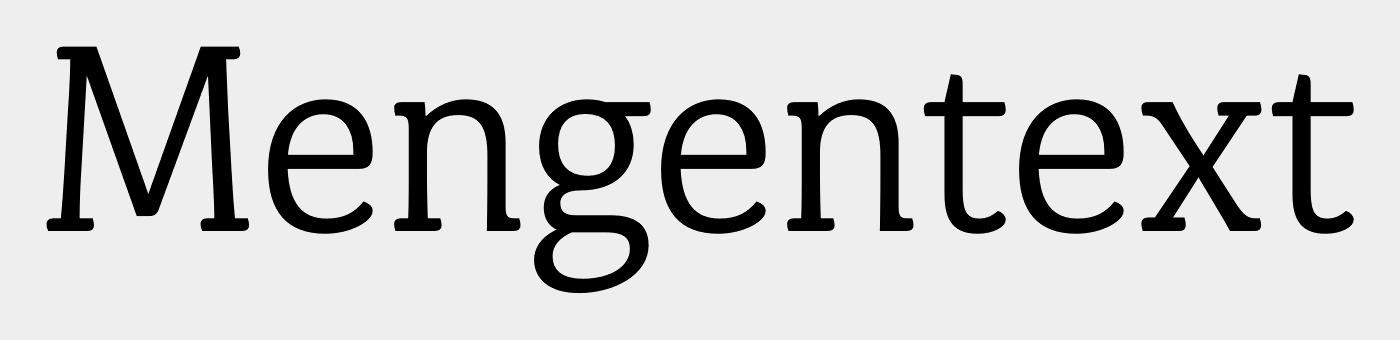
Gesucht: Font für Mengentext in lateinischer Schrift, vollständige diakritische Zeichen, Griechisch, Hebräisch, Arabisch, Äthiopisch
Wahrscheinlich suche ich die eierlegende Wollmilchsau, aber vielleicht gibt es ja die Schrift, die ich mit der Antipode von Paul Hanslow (http://typefacedesign.net/typefaces/year/2017/antipode/) bereits gefunden glaubte -- bis mir klar wurde, dass es die Antipode nur als Projekt, nicht aber als fertigen Font bzw. Fontfamilie gibt. Bestätigt wurde dies in einem sehr netten Mail-Austausch mit Paul,  den es derweil wohl ans andere Ende der Welt verschlagen hat (Kanada) und der zwar weiter an dem Projekt arbeitet, es aber noch nicht veröffentlichungsreif ausgearbeitet hat.
Bis dahin schlage ich mich also weiter herum mit einer Mischung aus verschiedenen Fonts, die alle ganz unterschiedliche Größenverhältnisse aufweisen, wenn ich zumeist Mengentext mit lateinischer Schrift vor mir habe, der zu erheblichen Teilen mit komplexen diakritischen Zeichen (Punkte, Häkchen, Striche unter und/oder über den Buchstaben) gespickt ist, garniert meist mit arabischen, hebräischen, äthiopischen (Fidäl), syrisch-aramäischen (Ost-/Westsyrisch), griechischen, kyrillischen, koptischen und mandäischen Textteilen. (Ich habe Semitistik [v.a. Äthiopistik und Aramaistik] und Evangelische Theologie studiert und arbeite jetzt in dem Bereich als freie Lektorin.)
Gibt es denn eine Schrift, die, das wäre mir das Wichtigste, weil am häufigsten gebraucht, zumindest die lateinischen Schriften, hübsche Mediävalziffern UND ein komplettes Syllabar der äthiopischen Schrift, inklusive der zusätzlichen amharischen Zeichen einer ästhetischen Güte ähnlich der Abyssinica SIL vereint?  :-?
Puh, äthiopisches Syllabar ist eine Herausforderung. Auf Anhieb fällt mir bei möglichst umfangreich und qualitativ höchstwertig die Andron ein. Sonst gibt es noch die hier und da etwas holprige Alphabetum, die auch die obskureren System beinhaltet.
Die Kefa (Systemfont von Apple) kann Amharisch …
… und Afrikaans, Albanisch, Amharisch, Asu, Baskisch, Bemba, Bena, Dänisch, Deutsch (Schweiz), Englisch, Estnisch, Färöisch, Filipino, Finnisch, Französisch, Friaulisch, Galicisch, Gusii, Indonesisch, Irisch, Isländisch, Italienisch, Kabuverdianu, Kalenjin, Katalanisch, Kinyarwanda, Kornisch, Luhya, Luo, Luxemburgisch, Machame, Madagassisch, Makhuwa-Meetto, Makonde, Malaiisch, Manx, Morisyen, Niederdeutsch, Nord-Ndebele, Norwegisch Bokmål, Norwegisch Nynorsk, Nyankole, Oromo, Portugiesisch, Rätoromanisch, Rombo, Rukiga, Rundi, Rwa, Samburu, Sango, Sangu, Schottisches Gälisch, Schwedisch, Schweizerdeutsch, Sena, Shambala, Shona, Soga, Somali, Spanisch, Suaheli, Suaheli (Kongo-Kinshasa), Taita, Teso, Tigrinya, Vunjo, Zulu.
Ich finde die Sprachlisten immer sehr unübersichtlich und irreführend, denn durch "Deutsch, Deutsch (Schweiz), Niederdeutsch, Schweizerdeutsch" werden diese Listen künstlich aufgebläht.
Die Code2000 kann alle diese Sprachen (und noch viele mehr), allerdings weiß ich nicht, wie das lizenztechnisch ist: Entwerfer und Downloadseite sind vor Jahren von der Bildfläche verschwunden; allerdings handelt es sich bei der Code2000 und ihren Schwestern um Share- bzw. Freeware, so dass das vielleicht unproblematisch ist.
PS: Leider ist die Schrift dafür am ästhetischen Ende nackt. – coangustatum est enim stratum ita ut alter decidat / et pallium breve utrumque operire non potest (Jes 28,20)
da waren ja schon sehr viele für mich neue Fonts und Hinweise, die ich teilweise (Rosetta) bereits kannte, aber vor Jahren dann wieder verbuddelt habe (Link- und Lesezeichenlisten als Vergessensgarant, verschwunden mit jedem neuen Computer), aber eben auch Neues.
Die Brill ist eine tolle Schrift, die auch regelmäßig nutze, aber eben meist in Verbindung mit Projekten, die für den Brill-Verlag gedacht sind. Harrassowitz oder Peter Lang kann ich damit nicht kommen :-o
Die SIL-Fonts sind bei mir in ständiger Benutzung, aber Antipode war schon, hach, vielleicht ... irgendwann ... Bei den kostenpflichtigen Varianten muss ich mich mal genauer umsehen, das ist super. Ich war ja auch etwas dreist damit, mehrere Fragen in einer unterzubringen. Und vielleicht ergibt sich aus der "Nachrecherche" des diesjährigen Typodarium-Kalenders, der ja ganz im Zeichen der Sprachenvielfalt steht, noch etwas.
Die bei mir zumeist verwendeten Fonts sind Junicode, ASTransfusion/AS_Transfusion, T, Charis SIL, Abyssinica SIL, SBL Hebrew, SBL Greek, Antinoou und Serto Batnan. Da diese aber teilweise noch aus meinen Unizeiten :-| stammen und anfangs sogar noch per Diskette weitergereicht wurden, wird es jetzt eben doch aller(aller!)höchste Zeit für mich, da mal etwas ... geordneter unterwegs zu sein, daher die Frage.
Ich vermute mal, dass Googles Weltschriftensuperfamilie Noto euch allen so selbstverständlich erschien, dass sie niemand erwähnen wollte? :-?  Stilistisch jetzt vielleicht nicht so interessant, aber dafür aktiv gepflegt und nicht de facto tot wie einige der anderen kostenfreien Optionen. Und du kannst zwischen Sans und Serif wählen.